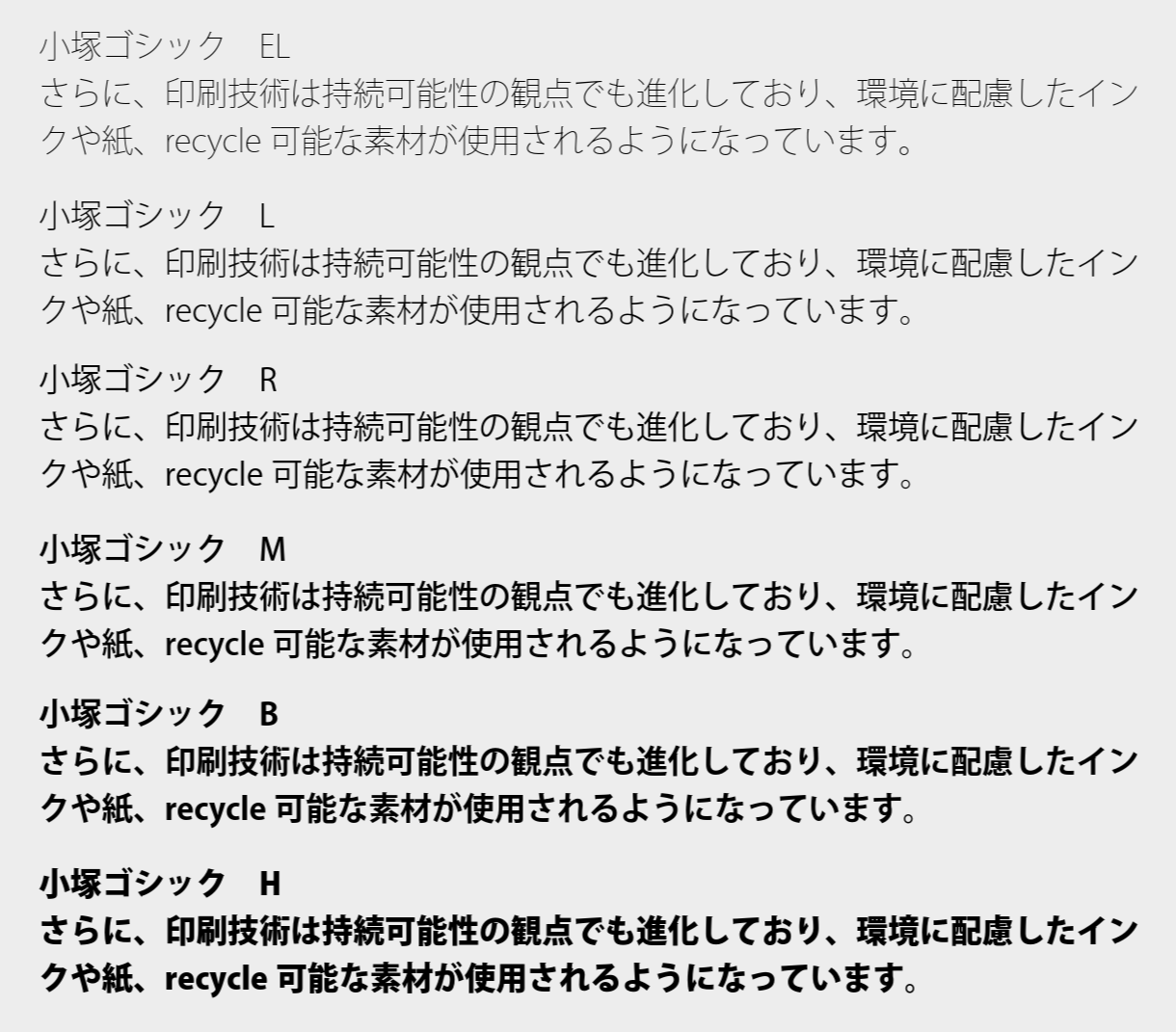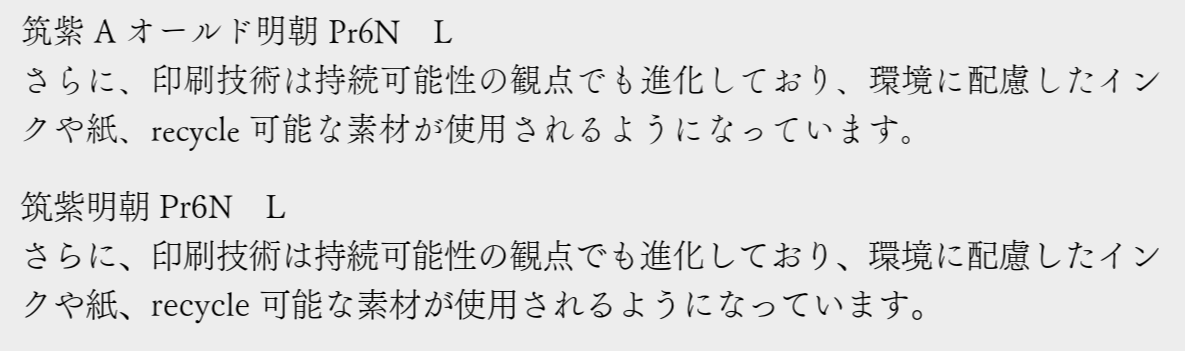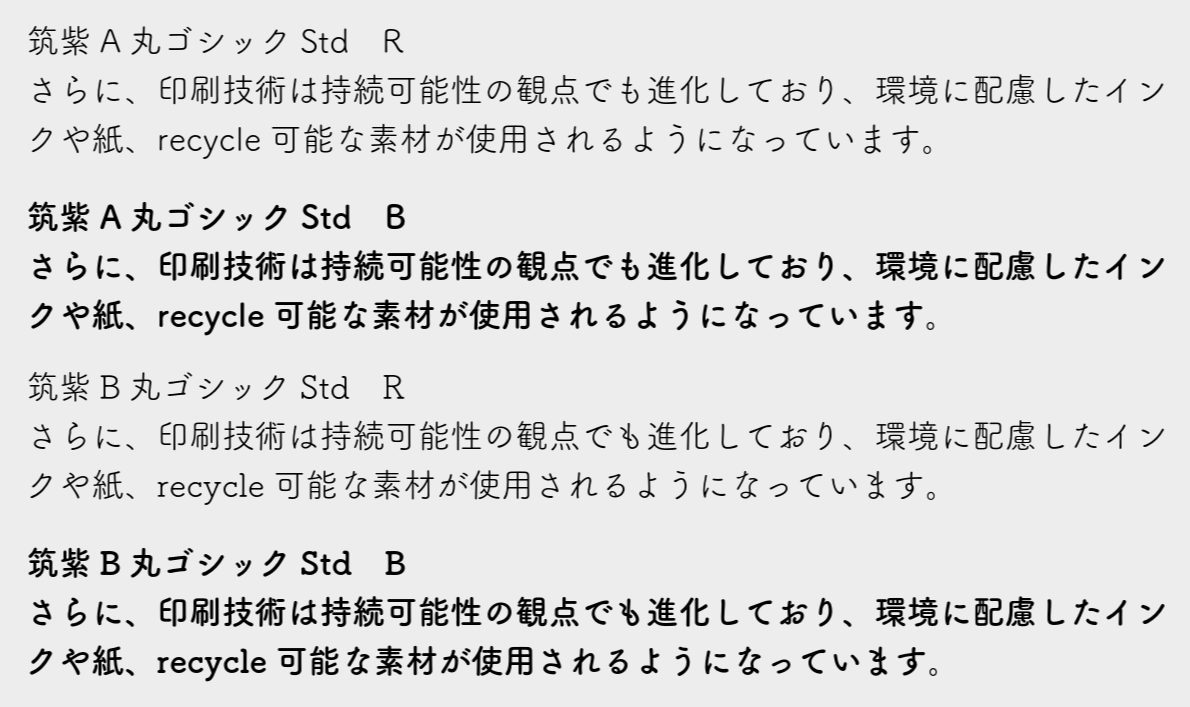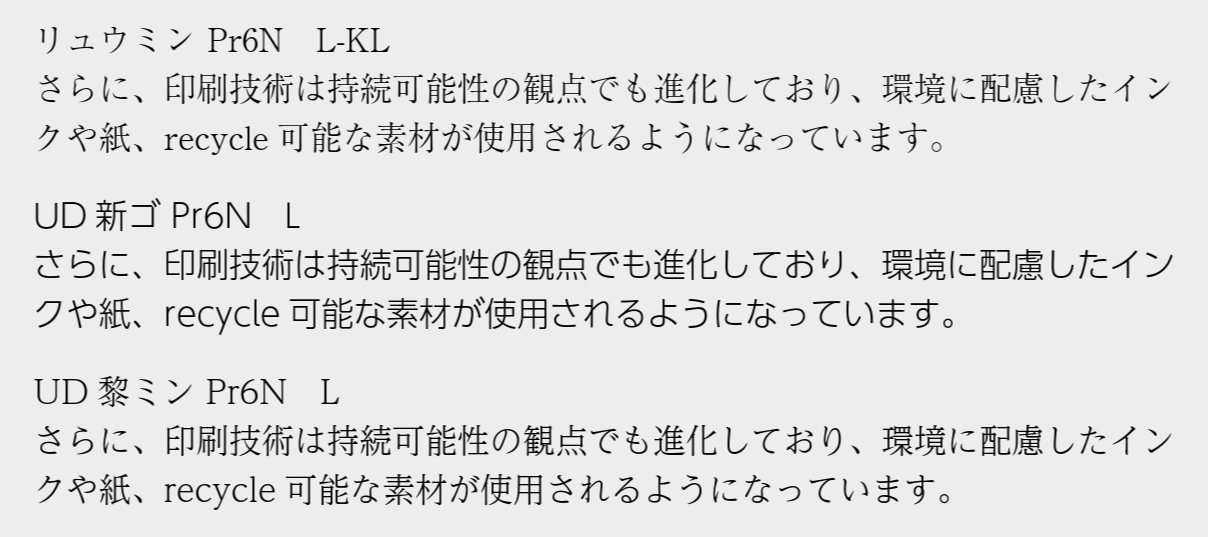
Wordのおすすめフォント|読みやすく美しい有料フォント7選
Wordには品質が高く、文書や資料の作成に十分なフォントが標準搭載されています。
しかし、より視認性に優れた雑誌や書籍、デザイン性の高い冊子の制作には外部フォントを使うこともあるでしょう。この記事では、有料で使用できる定番フォントを7種類紹介します。
小塚明朝
• Adobe系アプリに標準搭載
• ボールペン、シャープペンなど硬筆時代のモダンな明朝体
• 横組みに最適化された文字デザイン
• 視認性がよく、本文にも見出しにも使える
小塚ゴシック
• シンプルで端正なデザイン
• UIや資料、書籍にも向く
• 個性を抑えた読みやすい書体
• ウェイトが豊富で使いやすい
筑紫明朝
• フォントワークスの商用フォント
• 雑誌、書籍、広告でよく使われている
• 文字の造形が美しい
• 小塚明朝と比べると個性的
筑紫丸ゴシック
• ゴシック体はMacに標準搭載
• AとBのおもな違いは「かな」の書風
• 一般的な丸ゴシックと比べるとデザイン性が高い
• やさしい印象で読み心地があたたかい
その他の有名フォント(リュウミン、UD新ゴ、UD黎ミン)
リュウミン、UD新ゴ、黎ミン
• フォントメーカー「モリサワ」による書体で印刷・出版における基準
• 品質が高く、とても読みやすい
• 〈リュウミン〉は新聞や書籍で王道の明朝体
• Adobe系アプリでは〈新ゴ〉の代わりに〈UD新ゴ〉が使える